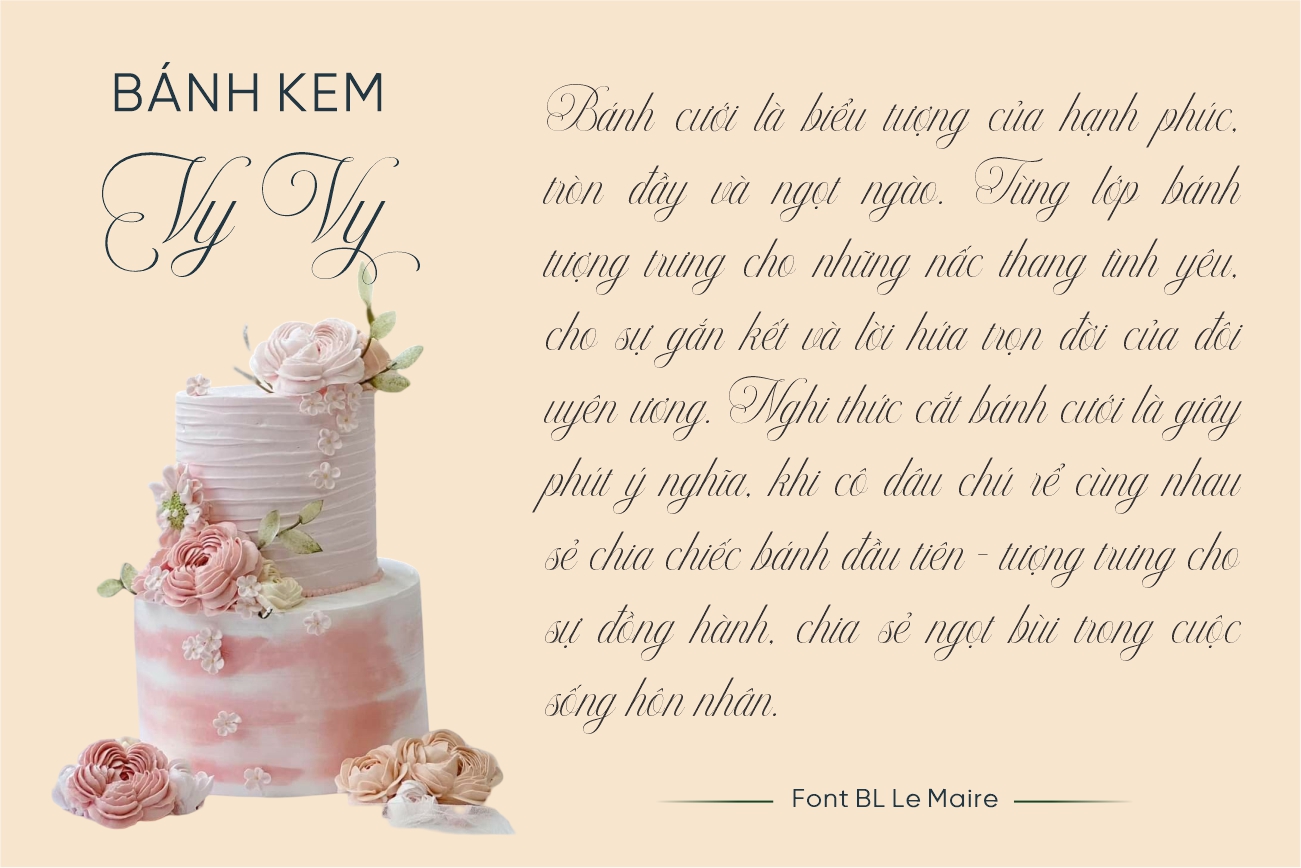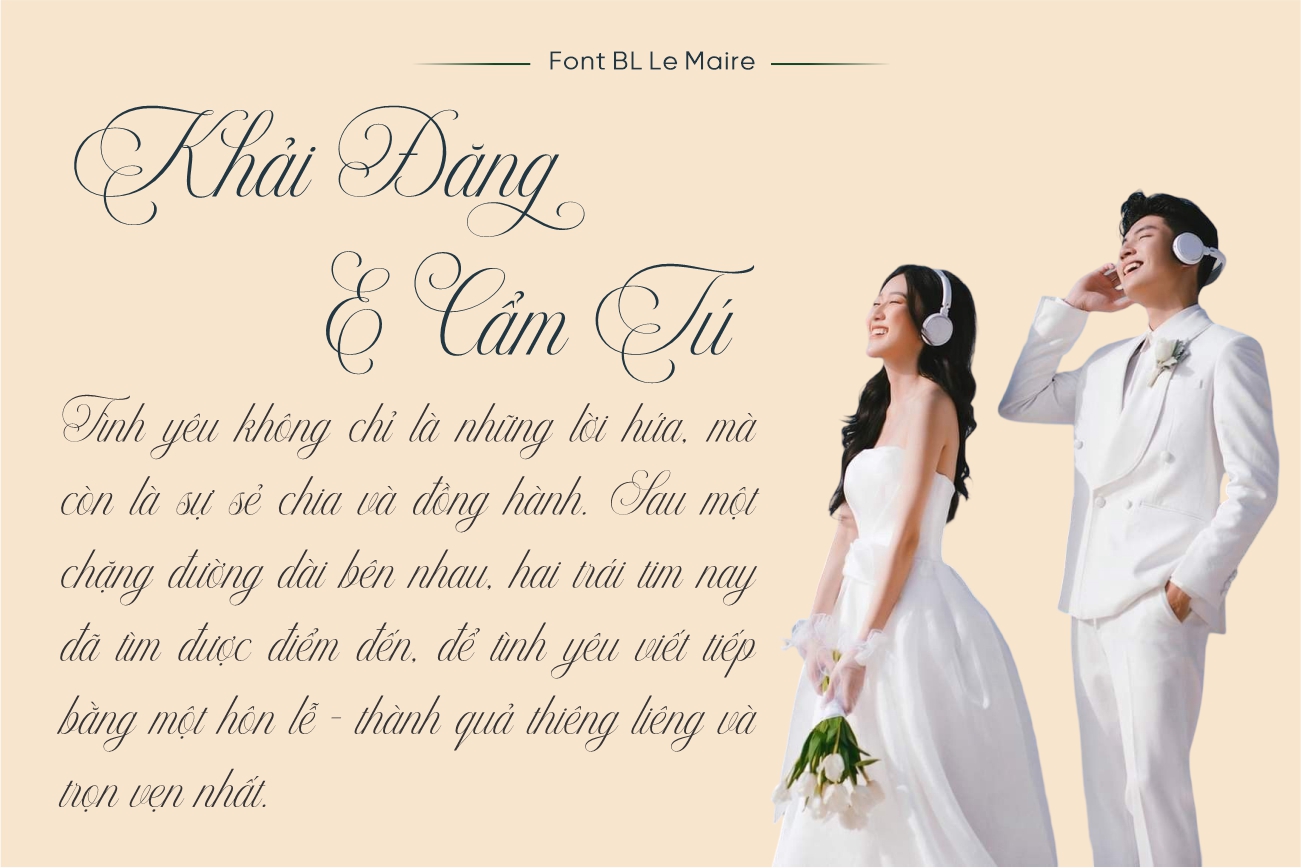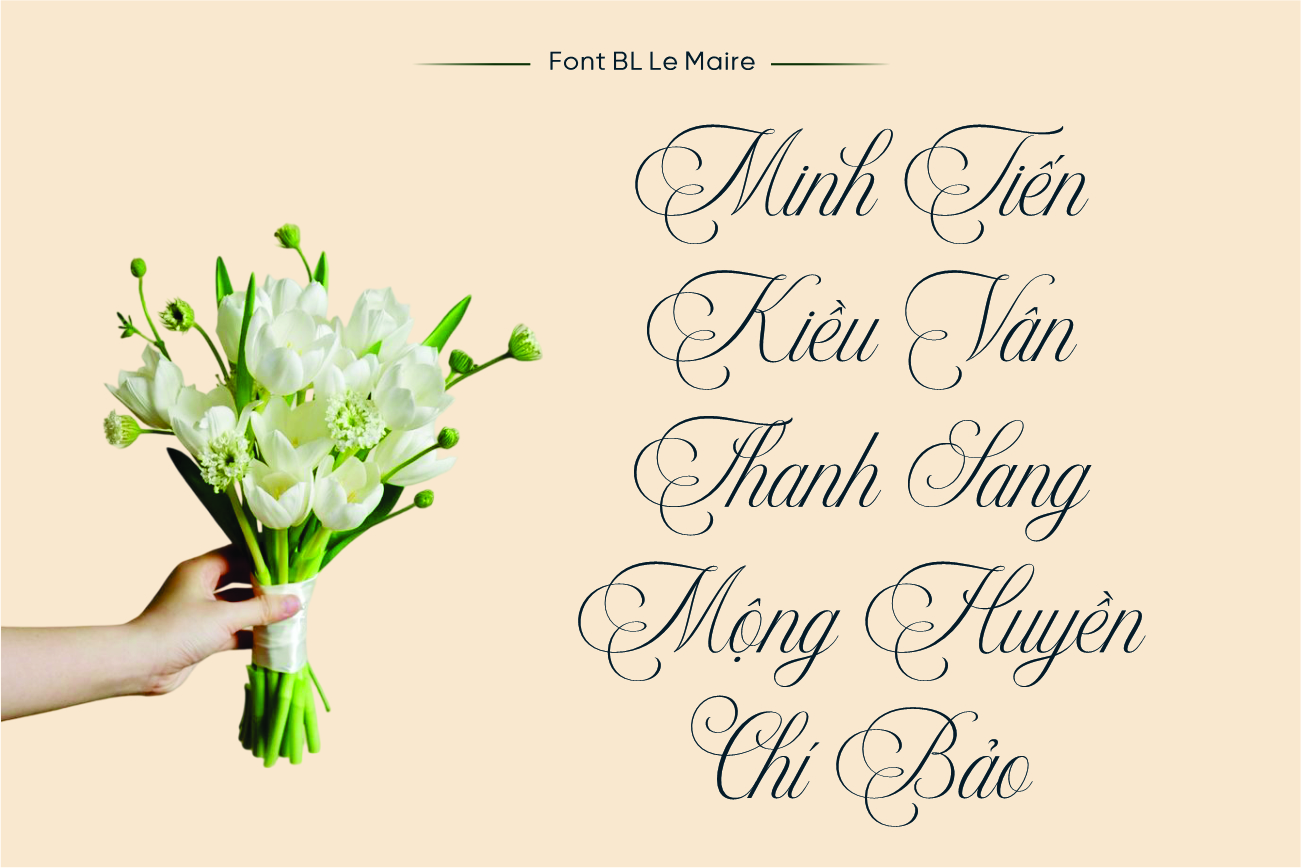
Font Chữ Đám Cưới Sang Trọng & Lãng Mạn Le Maire Việt Hóa
Trong thiết kế thiệp cưới, phông chữ đóng vai trò cực kỳ quan trọng để truyền tải thông điệp yêu thương và tạo nên dấu ấn riêng cho từng cặp đôi. Một font chữ đám cưới đẹp không chỉ mang lại sự tinh tế mà còn góp phần làm nổi bật phong cách của buổi lễ. Trong số đó, BL Le Maire Việt hóa là lựa chọn lý tưởng, mang đến cảm giác sang trọng, bay bổng và đầy lãng mạn.
BL Le Maire vốn là một thiết kế của Pixesia Studio, thuộc thể loại script calligraphy hiện đại. Với những nét chữ uốn lượn mềm mại, đường cong thanh mảnh cùng các flourish tinh tế, font mang đến vẻ đẹp quý phái, rất phù hợp để sử dụng trong thiệp mời cưới, menu tiệc, backdrop sân khấu hay bảng tên cô dâu chú rể. Sau khi được Team BL Việt hóa đầy đủ dấu tiếng Việt, font càng trở nên dễ sử dụng cho các nhà thiết kế trong nước, đảm bảo tính thẩm mỹ và chuẩn xác trong mọi nội dung.
Điểm nổi bật của phông chữ này là khả năng kết hợp hoàn hảo giữa sự lãng mạn và tính hiện đại. Không quá rườm rà nhưng vẫn giữ được nét uyển chuyển, BL Le Maire giúp người xem cảm nhận ngay được không khí hạnh phúc, trọn vẹn. Đây cũng là yếu tố khiến nó được đánh giá cao trong bộ sưu tập phông chữ đám cưới dành cho những thiết kế cao cấp.
Ngoài thiệp cưới, font còn được ứng dụng trong các sản phẩm khác như logo thương hiệu, bìa sách, poster nghệ thuật hay các ấn phẩm trang trí sự kiện. Nhờ sự linh hoạt này, BL Le Maire không chỉ là một font chữ, mà còn là công cụ sáng tạo giúp biến ý tưởng thiết kế thành tác phẩm nghệ thuật.
Nếu bạn đang tìm kiếm một font chữ đám cưới vừa đẹp, vừa chuẩn Việt hóa, thì BL Le Maire chắc chắn là lựa chọn không thể bỏ qua. Đây là phông chữ đám cưới lý tưởng để biến mọi thiết kế ngày trọng đại trở nên thật sự khác biệt và đáng nhớ.